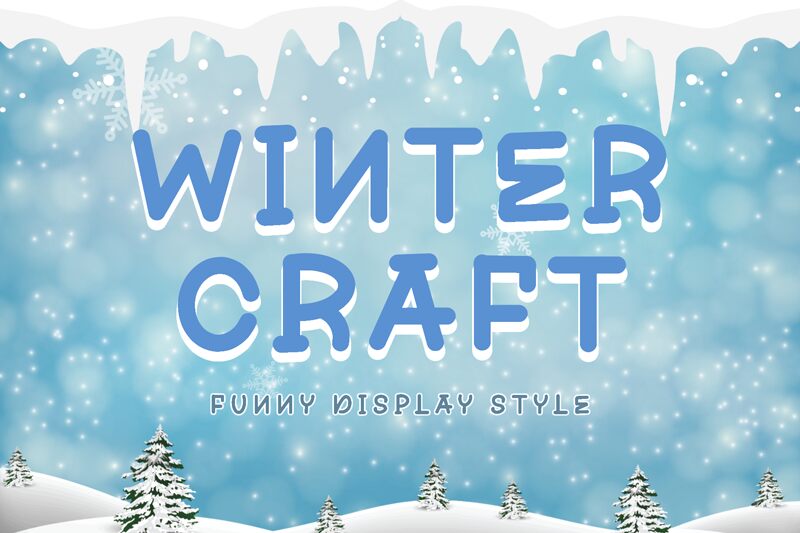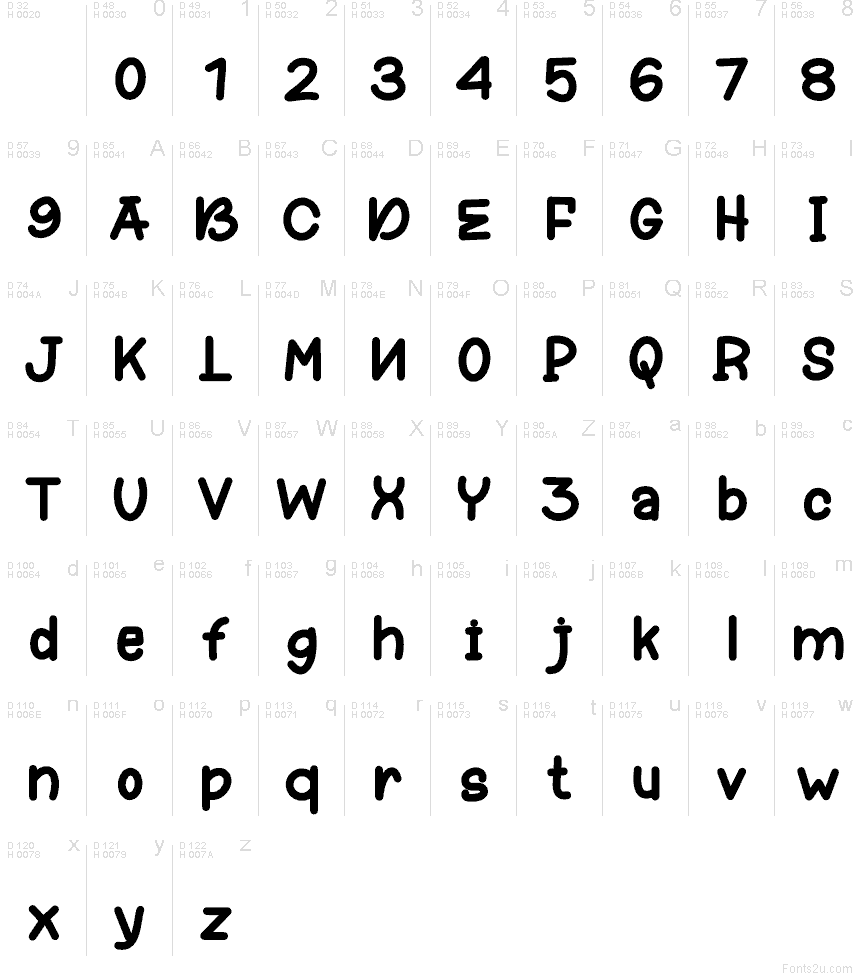
Winter Craft Demo
Winter Craft Demo je bezplatné komiksové písmo s oblými tvarmi a jemným, ručne kresleným rytmom. Písmená pôsobia mierne nepravidelne a uvoľnene, pričom ich jednoduché tvary dodávajú dizajnu priateľský a remeselný nádych.
Winter Craft Demo skvele využijete na sviatočné pohľadnice, sezónne plagáty, obaly pre deti, nálepky, grafiku na sociálne siete alebo ceduľky na remeselné trhy. Oblá štruktúra zaručuje príjemný vzhľad a zároveň poskytuje dostatok charakteru pre krátke nadpisy, etikety a dekoratívne prvky.